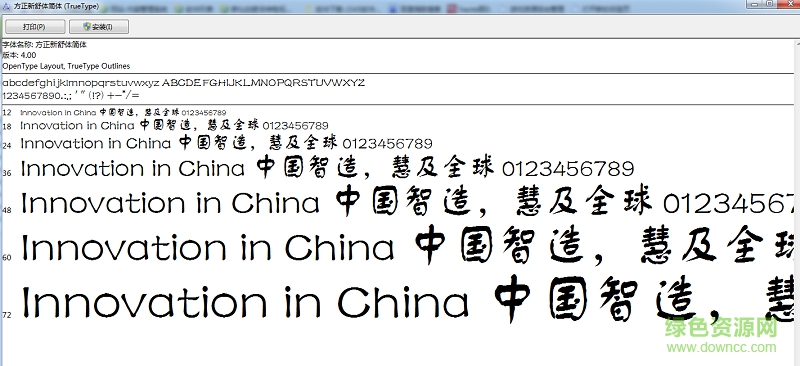
fznstjwgb10字體是一款很美觀的字體,這款字體字形飄逸,但是也不像正楷字體那么嚴(yán)肅,一筆一劃之間有中活潑的韻味,感興趣的朋友就來綠色資源網(wǎng)下載吧!
fznstjwgbk字體是一款方正出品的gbk字體,藝術(shù)設(shè)計、海報設(shè)計、美工等都可以使用,字體簡潔耐看、工整流暢。